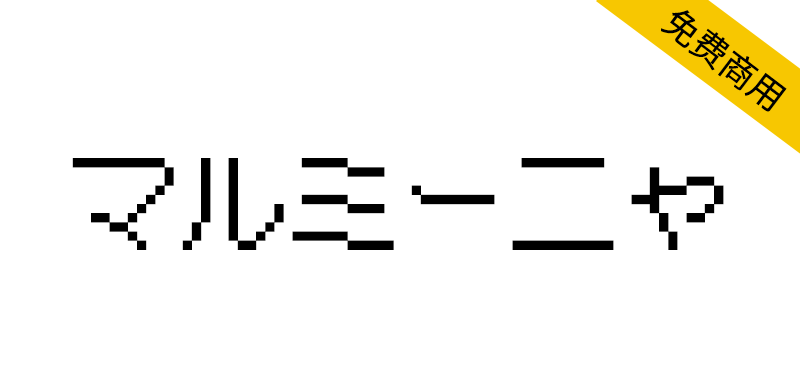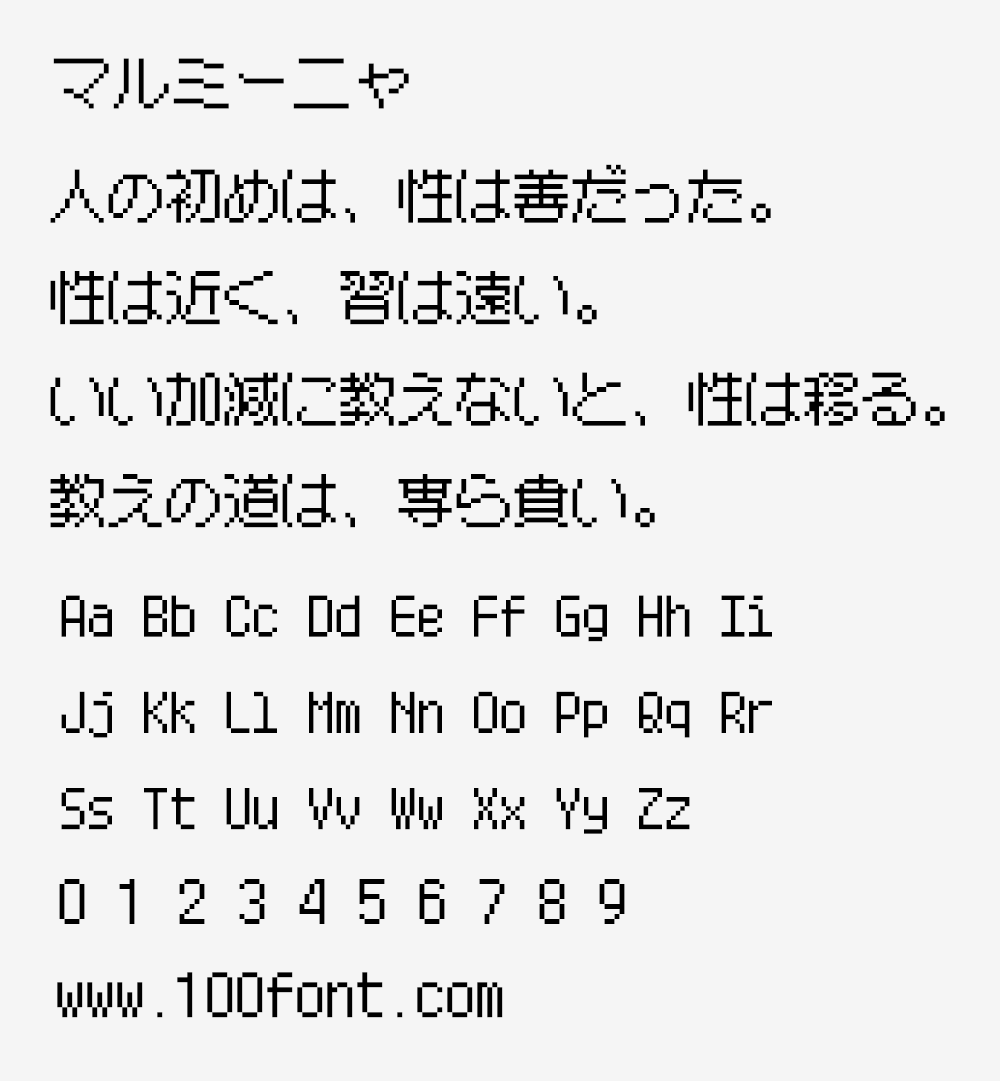
MaruMinya(マルミーニャ)是一个基于12像素大小的圆形哥特体像素字体,具有大字形和广泛留白的特点,通过整齐排列的像素布局实现了良好的可读性。“可爱”中也有“认真”,是可以在广泛的用途中贴近像素表现的字体。
充实的汉字收录数,收录JIS第一水平汉字2965字、第二水平汉字3390字,印刷标准字体也对应,适合包含广泛的汉字的日语文本。※不支持竖写。
■ピクセルのかわいさ、詰め込みました。
12ピクセルサイズをベースにした、丸ゴシック体ピクセルフォントです。
大きな字面と広いフトコロを持ち、整理されたピクセルの配置により、十分な可読性を発揮します。
「かわいさ」の中にも「まじめさ」があり、幅広い用途でピクセルの表現に寄り添うことができるフォントです。
■充実の漢字収録数。
JIS第1水準漢字2965字、第2水準漢字3390字を収録。
印刷標準字体にも対応、幅広い漢字を含む日本語テキストに適しています。
※縦書きには非対応となっています。